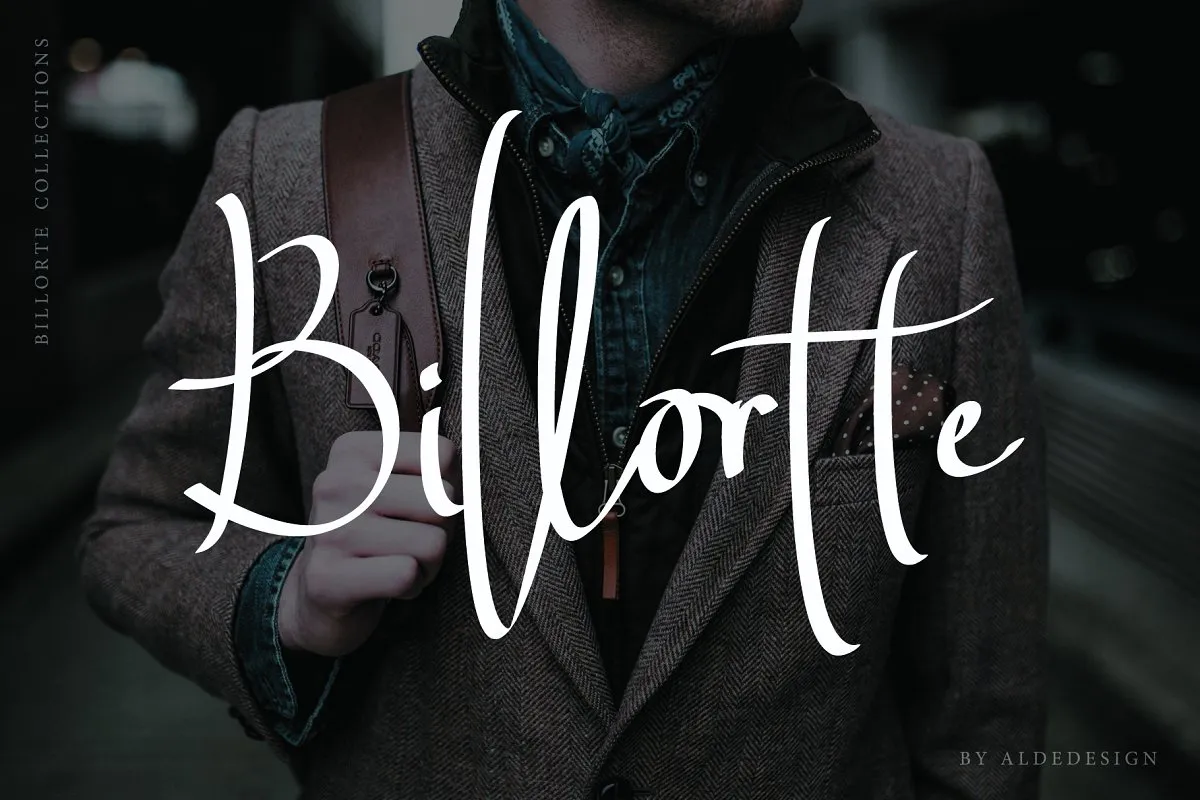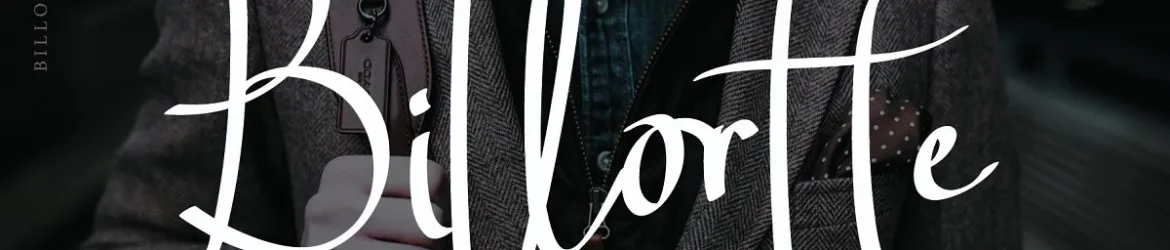
Billortte Script Font – Download Grátis
A fonte ‘Billortte Script Font’ é uma escolha perfeita para aqueles que buscam um tipo elegante e sofisticado. Seu estilo manuscrito com base clássica traz elegância sem excessos, oferecendo duas variações elegantes. Os recursos do OpenType incorporam detalhes como ligaturas, tornando a fonte ainda mais versátil. Com uma aparência refinada e acessível, o Billortte é perfeito para aplicativos que incluem logotipos de marcas, design de livros capa, selos de foto, cartões de negócios e muito mais. A simplicidade elegante do ‘Billortte Script Font’ certamente faz a sua marca brilhar em qualquer projeto gráfico.